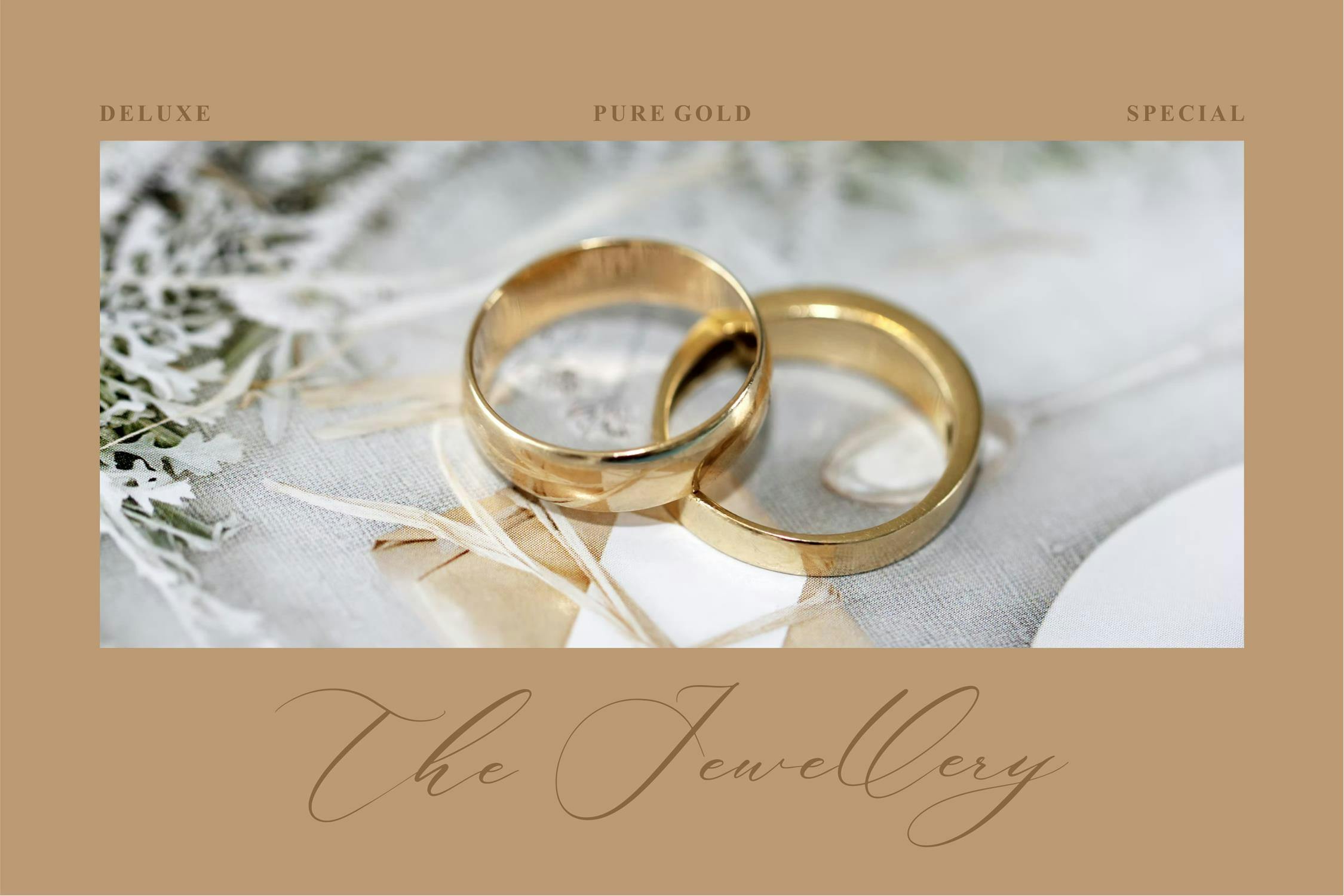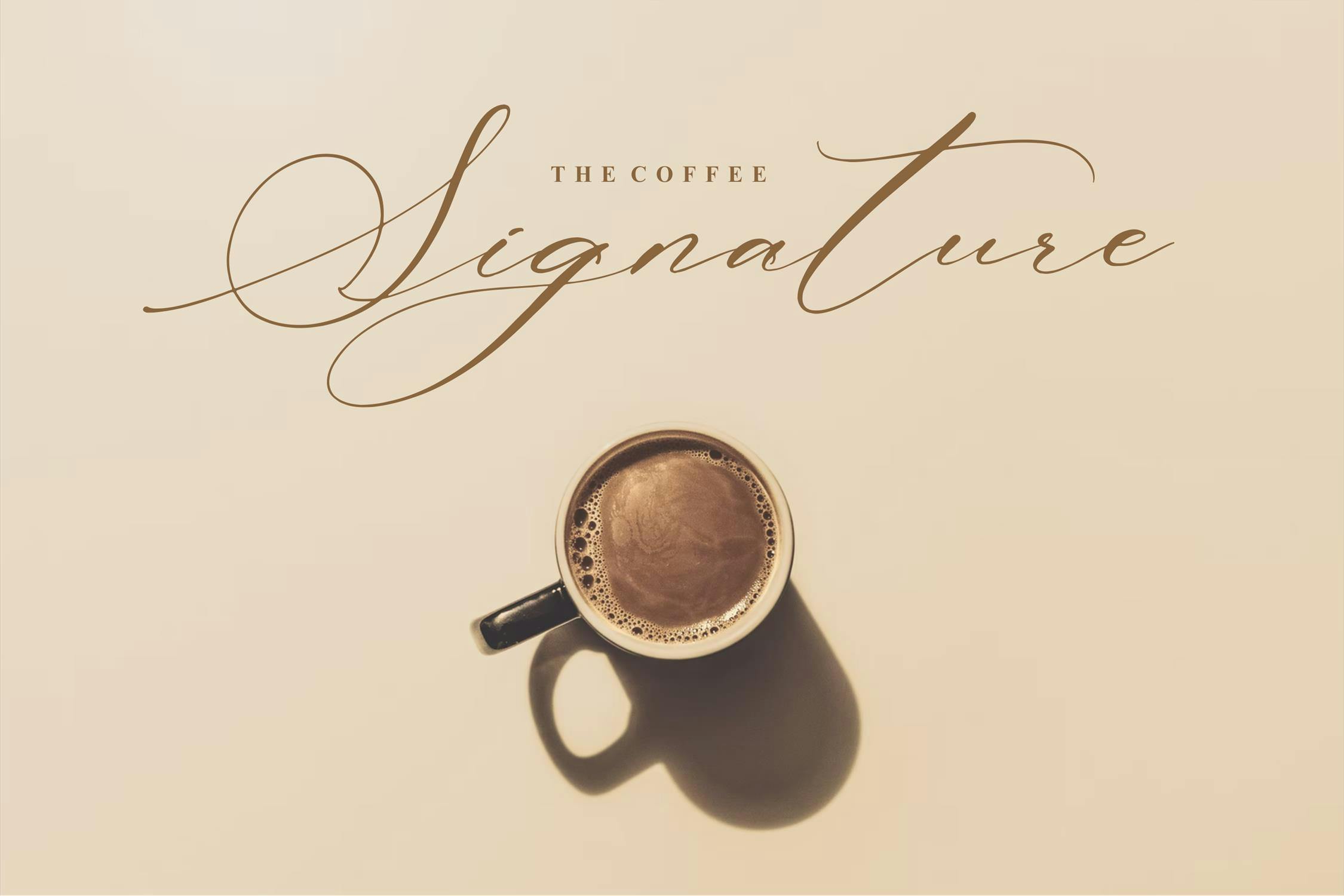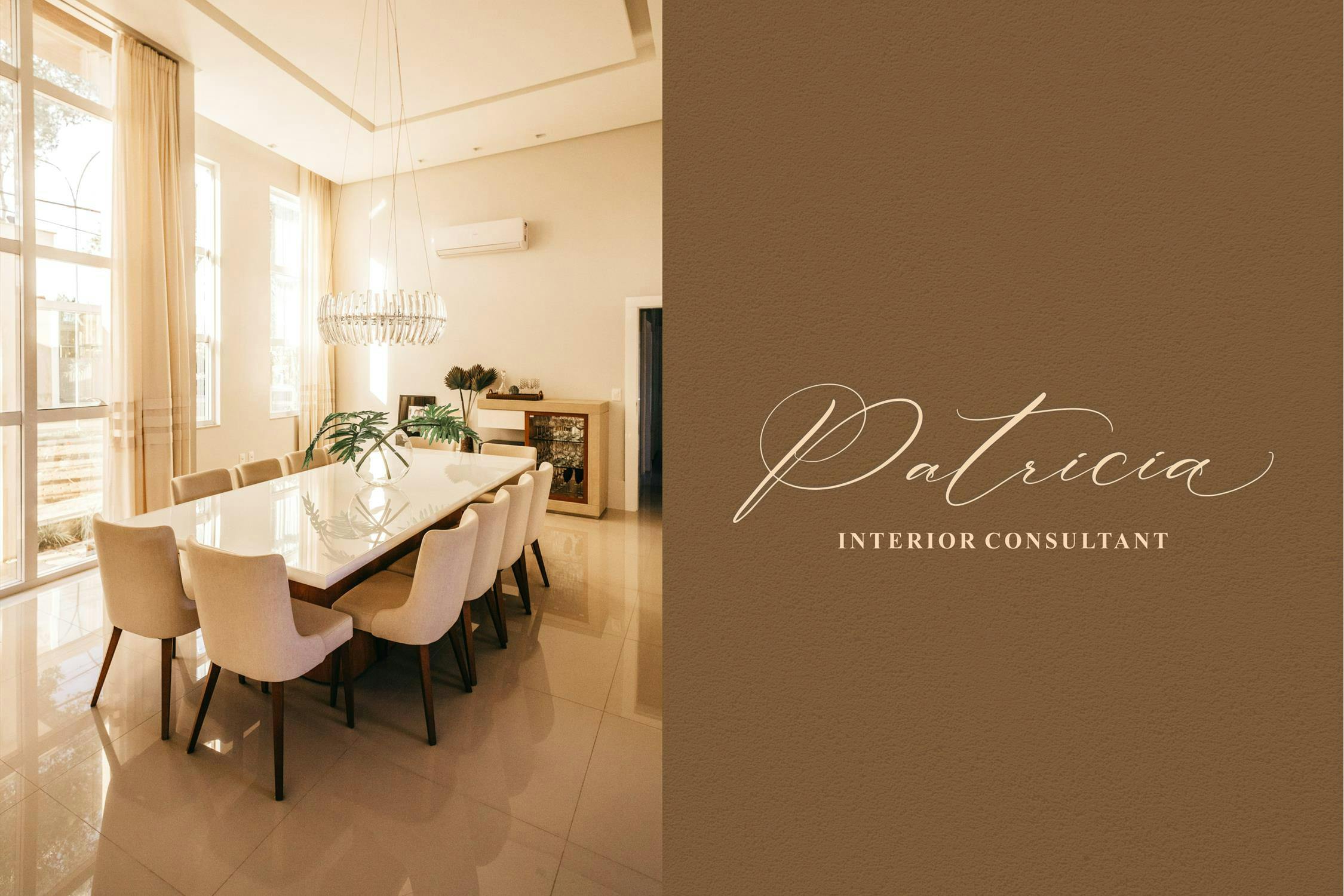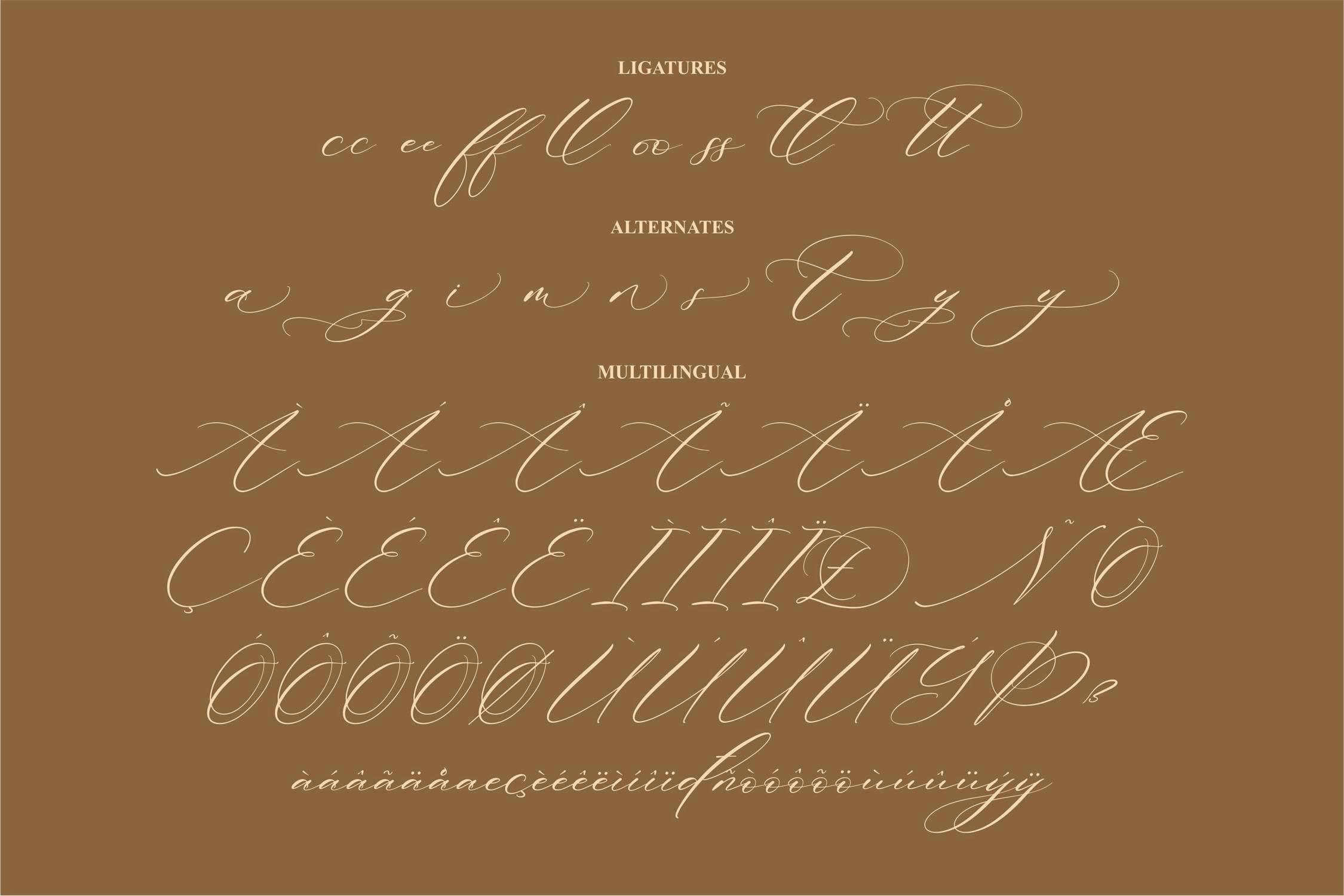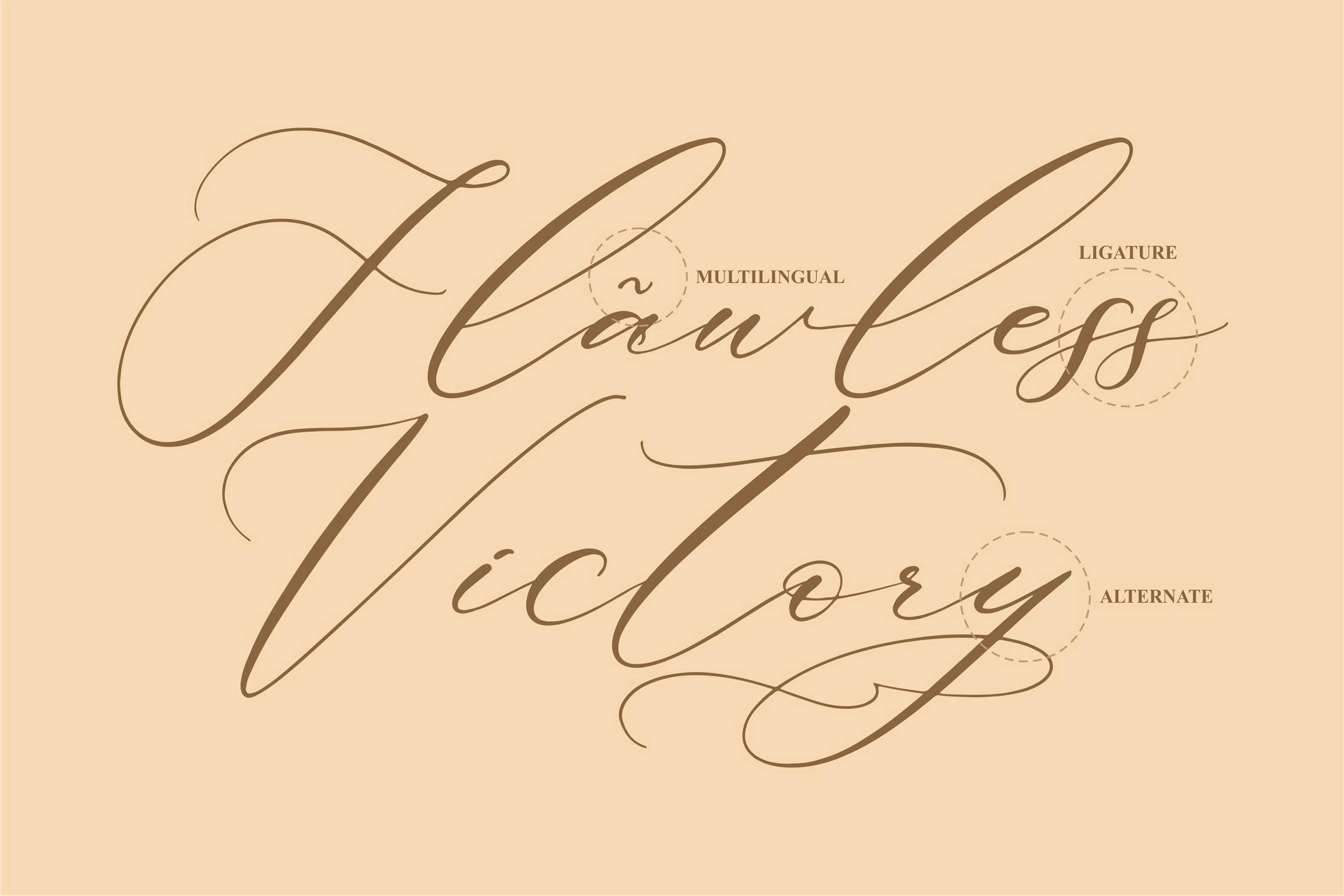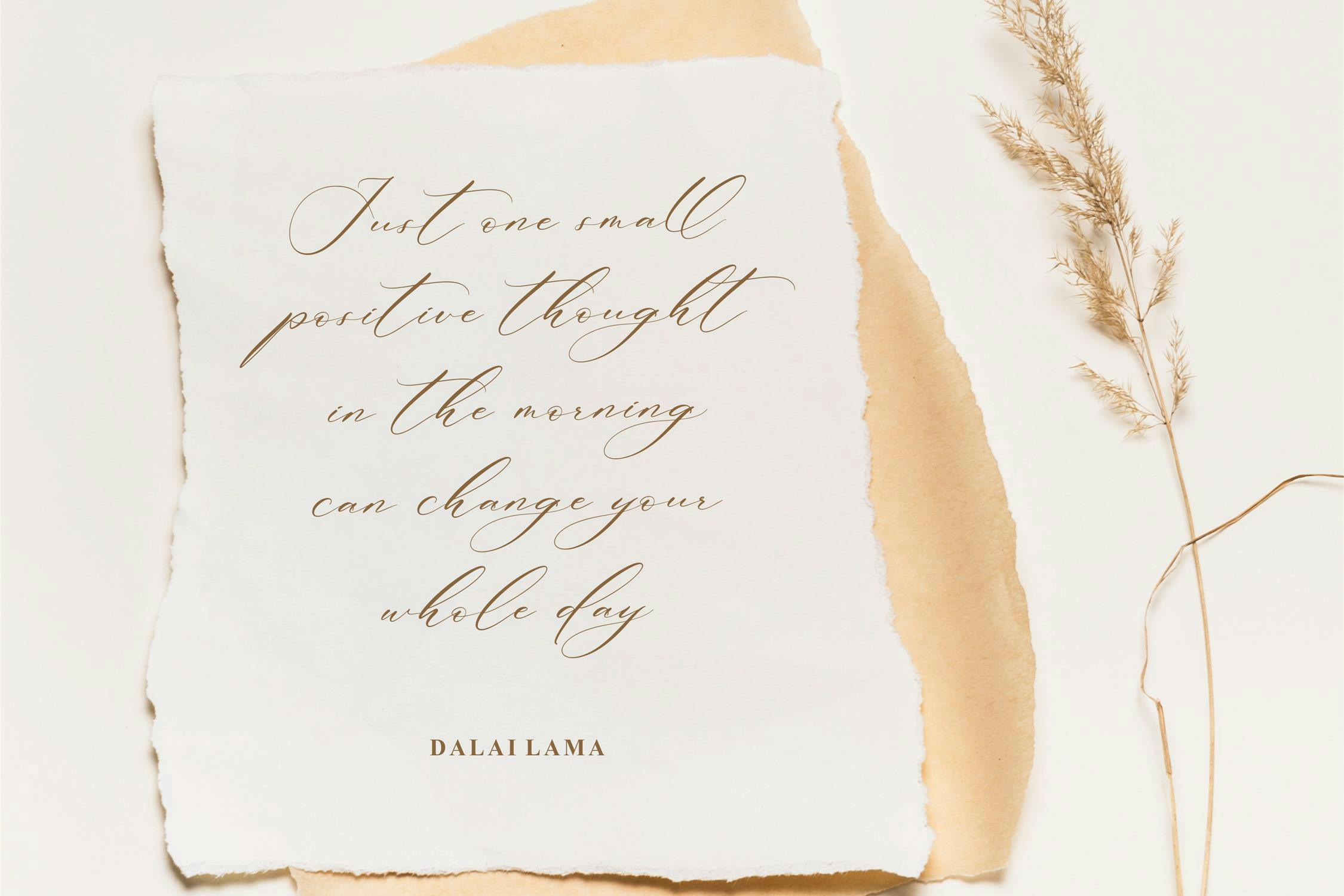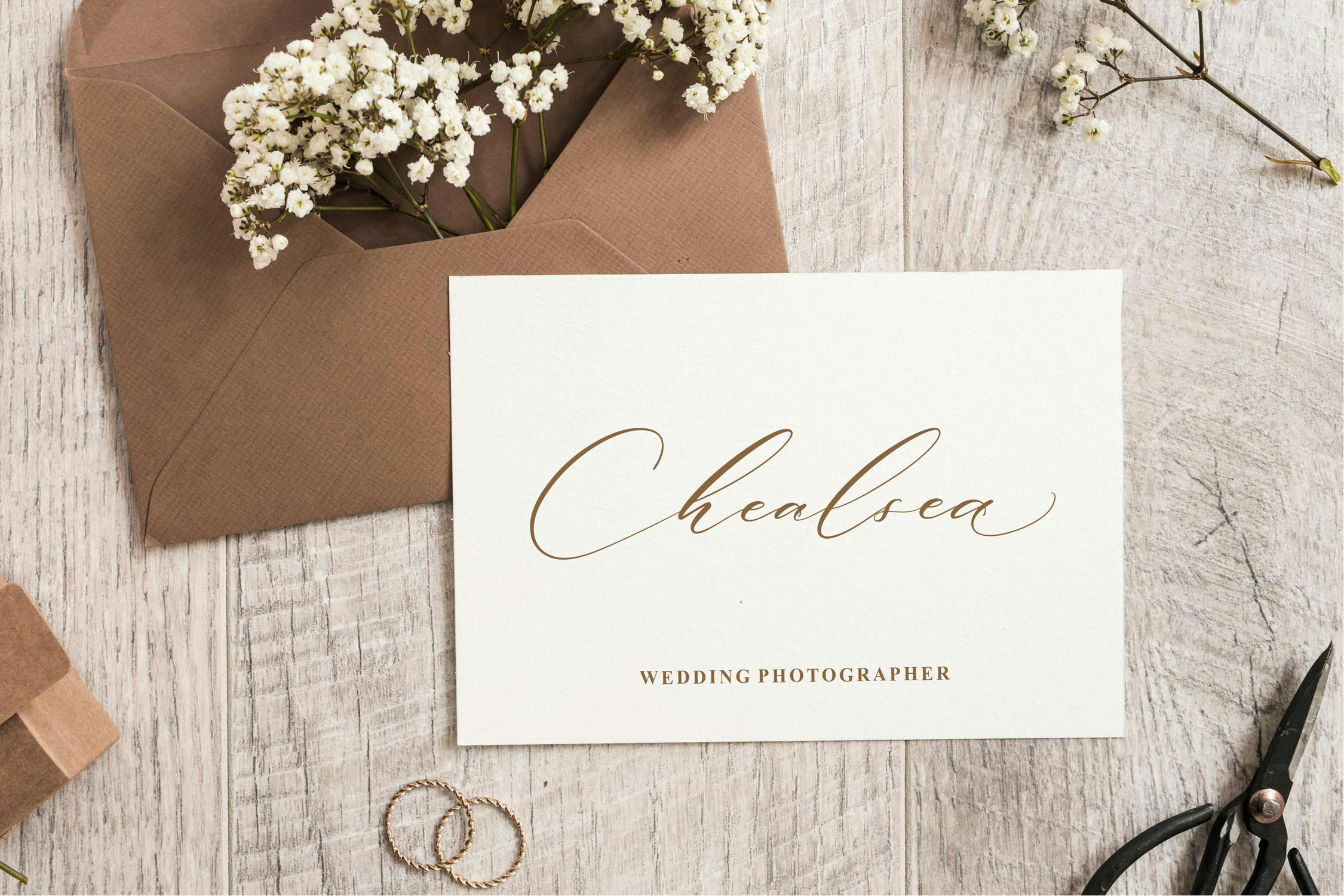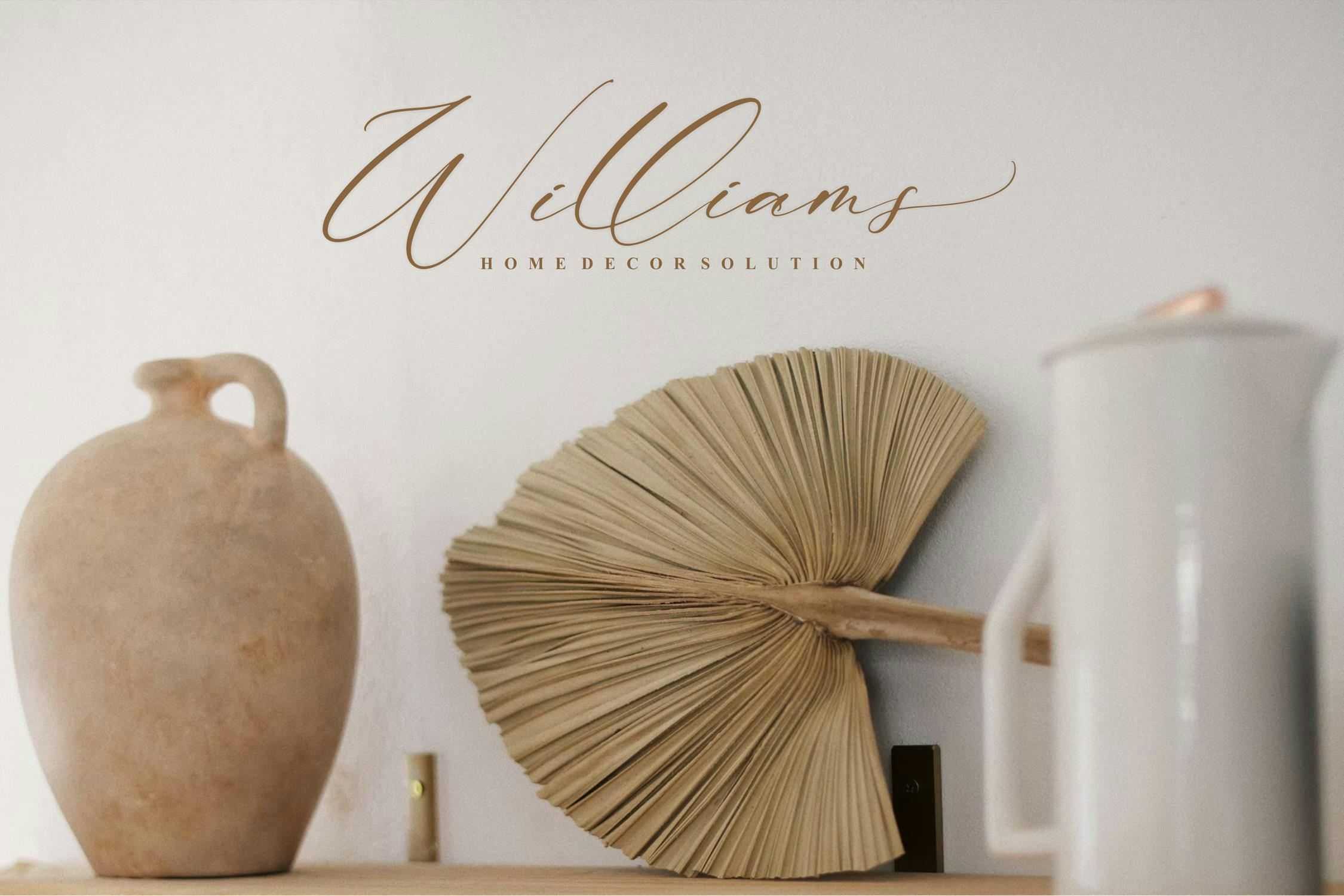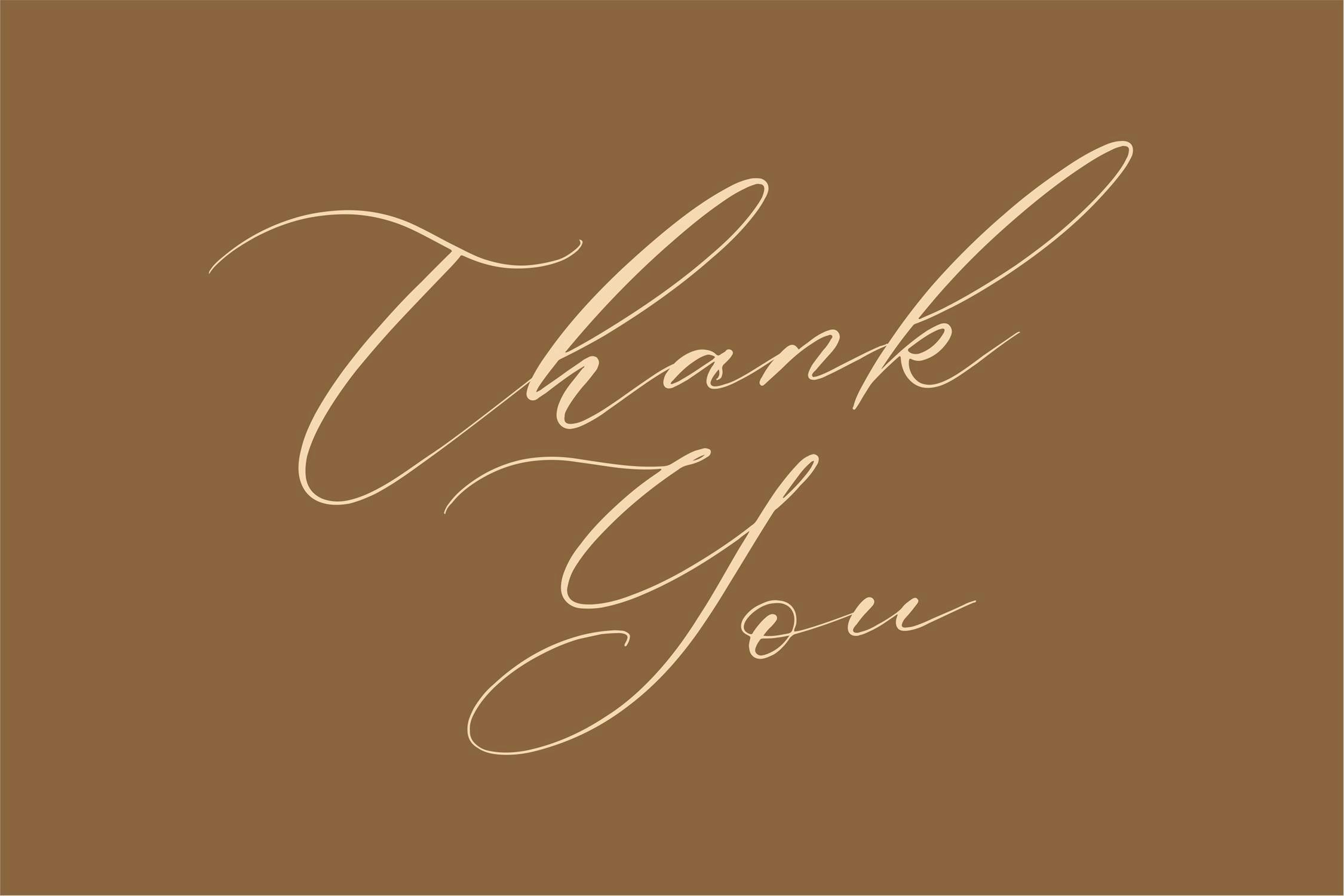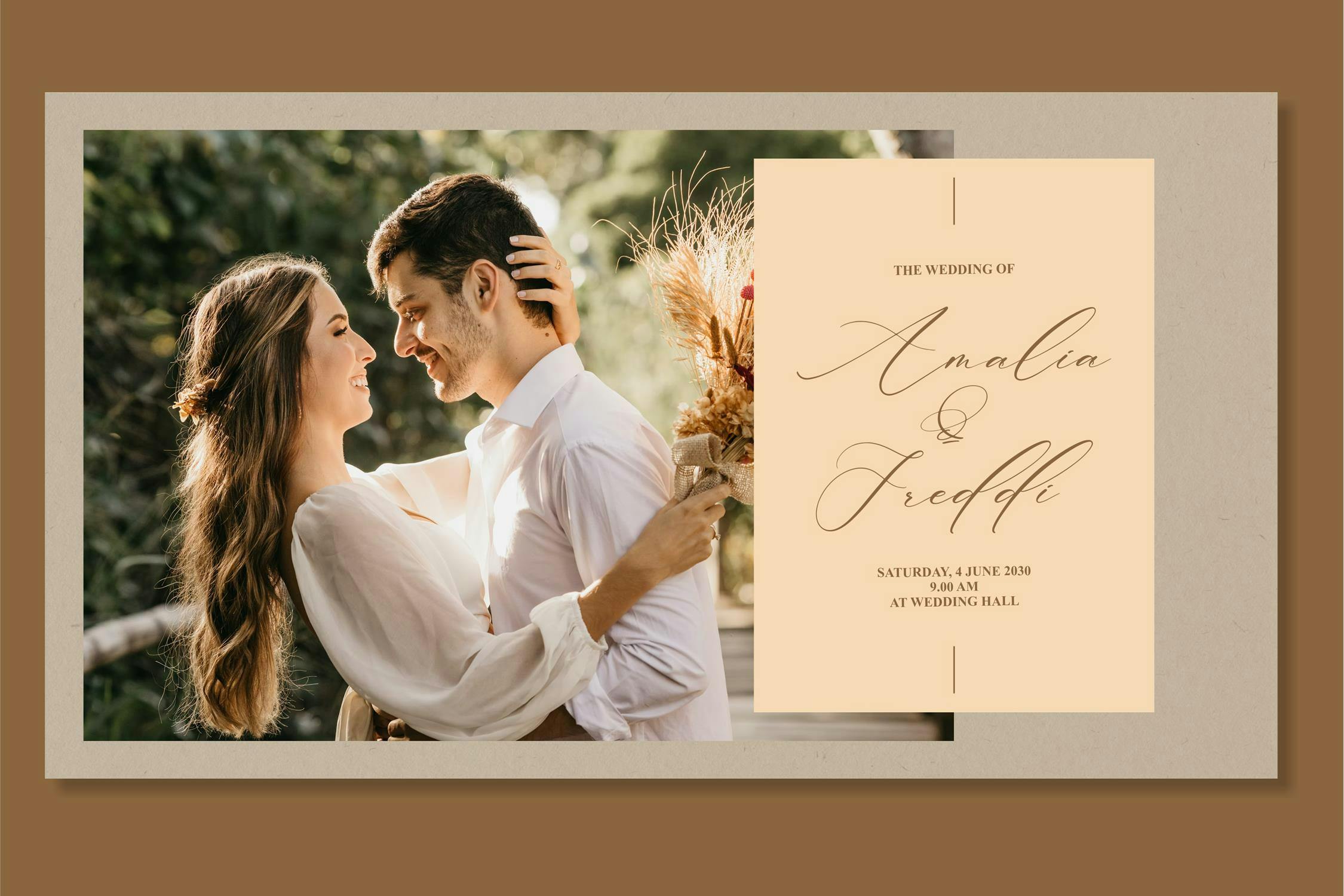
Patricia Rustine Luxury Script Font
فونت پتریشیا راستین، انتخابی ایده‌آل برای پروژه‌های خلاقانه شما.
این فونت برای پوسترها، پست‌های شبکه‌های اجتماعی، برندینگ، پروژه‌های شخصی و غیره ایده‌آل است.